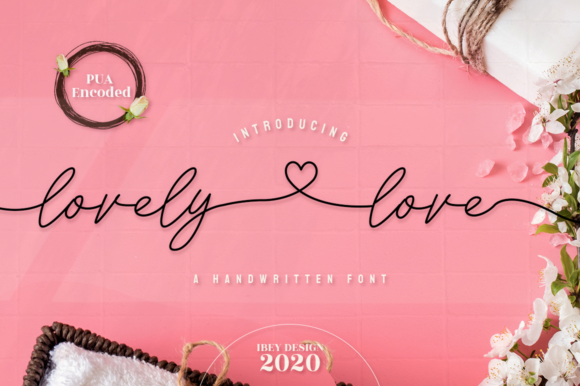
Lovely Love в равной степени очаровательна и элегантна.
Он потрясающе смотрится на свадебных приглашениях, благодарственных открытках, цитатах, поздравительных открытках, логотипах, визитных карточках и любом другом дизайне, который нуждается в рукописном штрихе.
Этот шрифт закодирован в PUA, что означает, что вы можете легко получить доступ ко всем глифам и штрихам!
Он имеет изменяющуюся базовую линию, плавные линии, великолепные глифы и потрясающие альтернативы.